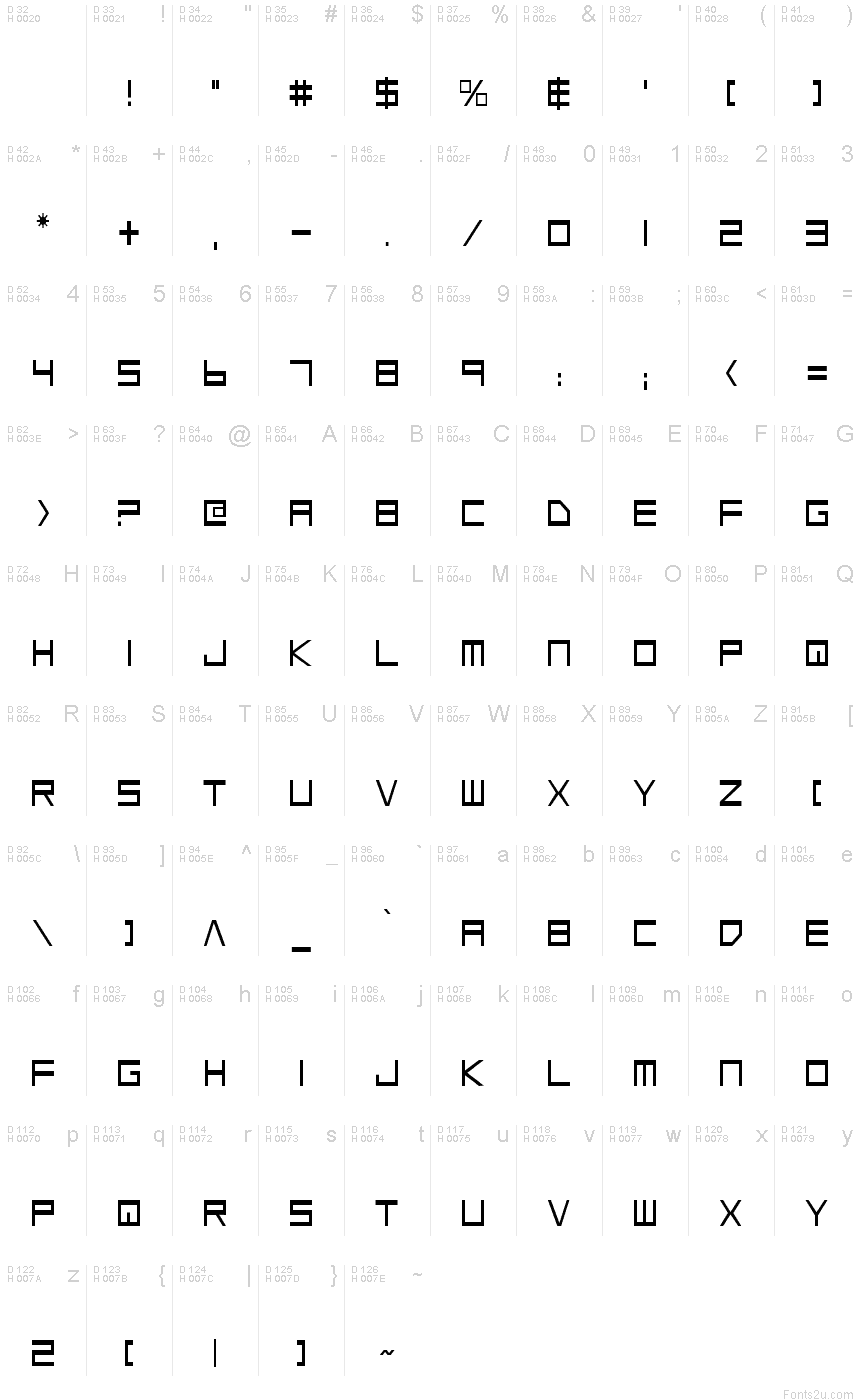
Low Gun Screen Condensed, di Iconian Fonts, è un font display gratuito in stile techno, costruito su angoli retti rigidi e una geometria che ricorda quella degli schermi. Le sue maiuscole presentano proporzioni alte e strette, forme squadrate e interruzioni strategiche che conferiscono al lettering il ritmo serrato di un'interfaccia arcade.
È perfetto per loghi di videogiochi, poster sci-fi, branding esports, copertine di album e titoli di interfacce, dove la sua silhouette modulare trasmette un tema deciso. Essendo un font gratuito, funziona particolarmente bene per i titoli brevi, lasciando che le sue giunture nette e le forme squadrate siano le vere protagoniste.
Low Gun Screen Condensed